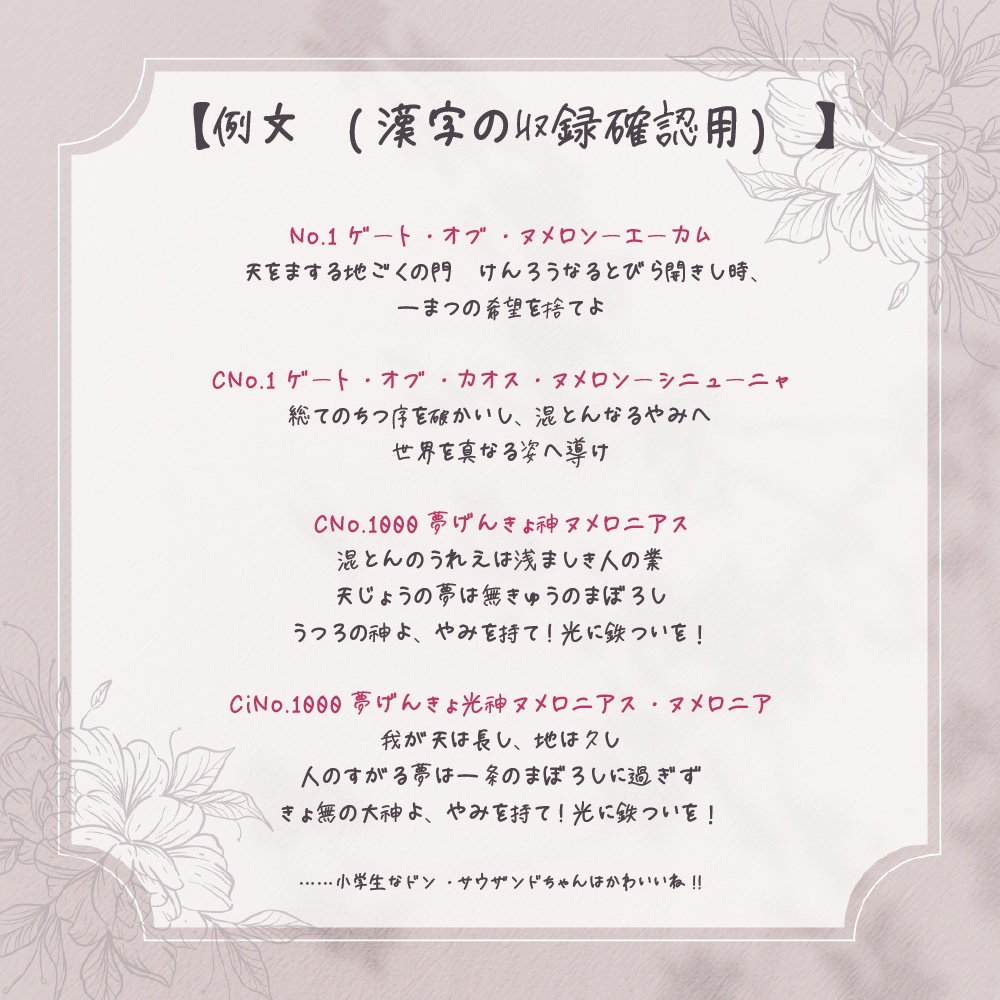
【フリーフォント】『OLナハトさん』
【2025.06.28】追記 有料版(中学漢字+430文字程度を追加、太さ統一版)を公開いたしました! https://nacht-7810.booth.pm/items/7108054 良ければどうぞ✨ 湊月ナハトの手書き文字をフォントにしてみました。 漢字は小学校で習うもののみ収録しています。 『OLナハトさん』とか言いながら小卒です。 諸事情により、Godの「神」は旧字体です。 ……なんででしょうね?(笑) 手書きフォントなので、字によっては大きい・小さい・太い・細いetc...あります。 ガタガタなのも味…だよネ!と楽しめる方にオヌヌメロンです。 ハンドメイド雑貨のサンクスカードとかに良いんじゃないでしょうか。 ※このフォントは『iFontMaker』というアプリケーションで作成しました。 ■対応文字 アルファベット(全角/ウムラウト等も対応)・ひらがな・ カタカナ(全角)・数字・教育漢字を収録 ■DLデータ(Zipファイルですので、解凍してご利用ください) OL NachtSan.ttf 一点 ■注意事項 趣味で作成したものなので、商用利用等は禁止いたします。 フォントの再配布(埋め込み等でフォントデータをダウンロードできる状態にしていることも含む)も禁止です。 あくまでも趣味の範囲で、良識ある使い方をお願い致します。 ※YouTube動画制作者さん(収益化済みチャンネルも含む)、Instagram等で活動されている投稿者さん、ハンドメイド作家さん等は、収益がある場合でもご利用いただけます。